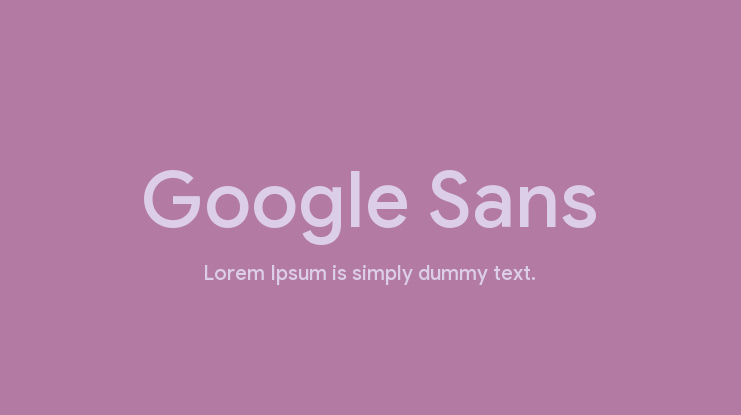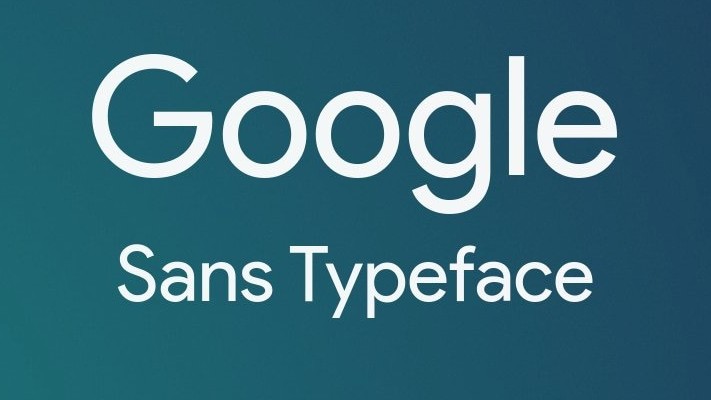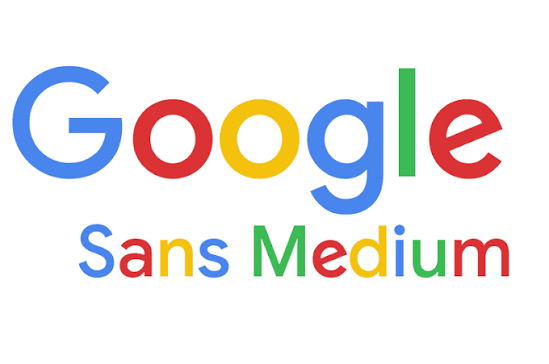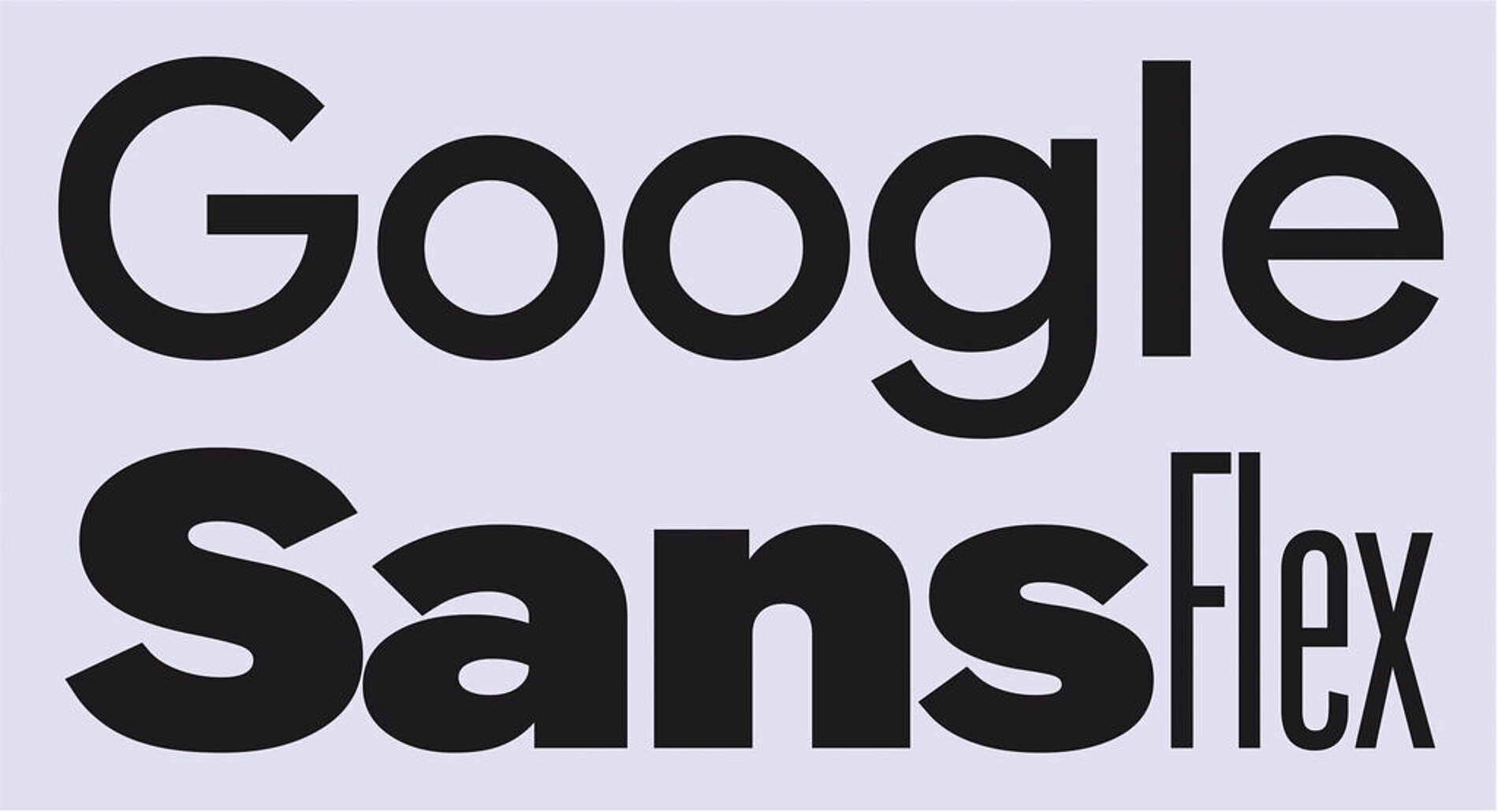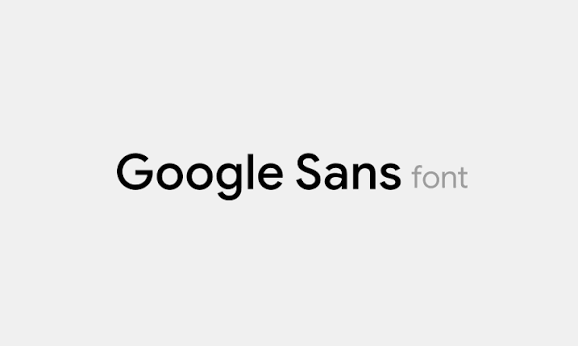
Google Sans là phiên bản tùy chỉnh của bộ phông Product Sans, được Google thiết kế tối ưu cho việc hiển thị trên đa dạng nền tảng từ thiết bị di động đến các ấn phẩm in ấn khổ lớn. Với cấu trúc hình học chuẩn xác và vẻ ngoài thân thiện, việc download font Google Sans giúp các nhà thiết kế, kiến trúc sư trình bày nội dung văn bản một cách chuyên nghiệp, hiện đại.
Google Sans
Sự tinh tế trong ngôn ngữ thiết kế của bộ font Google Sans
Điểm thu hút đặc trưng của Google Sans nằm ở sự cân bằng hoàn hảo giữa các đường nét hình học và tính nhân bản. Khác với những phông chữ không chân truyền thống thường có cảm giác hơi thô cứng, Google Sans sở hữu các góc bo nhẹ nhàng và khoảng hở giữa các chữ cái được tính toán khoa học. Phiên bản tải font Google Sans Việt hóa đã được xử lý kỹ lưỡng hệ thống dấu thanh tiếng Việt, giúp các ký tự đặc biệt phối hợp nhịp nhàng với thân chữ, duy trì vẻ đẹp tinh gọn và sang trọng của bộ gốc.
Sự ổn định về mặt thị giác còn giúp phông chữ này trở thành lựa chọn ưu tiên cho các nội dung cần độ minh bạch cao. Dù được sử dụng cho tiêu đề chính hay các đoạn thuyết minh kỹ thuật, bộ phông vẫn giữ được độ sắc nét và sự rõ ràng cần thiết. Đây là phương án hiệu quả để thể hiện tư duy sáng tạo hiện đại, phù hợp với xu hướng kiến trúc tối giản và các giải pháp xây dựng thông minh hiện nay.
| Phân loại phong cách | Geometric Sans-serif / Modern Style |
| Lĩnh vực phù hợp | Website, Portfolio dự án, Bảng hiệu công trình |
Tư vấn lựa chọn: Google Sans đạt hiệu quả thẩm mỹ cao khi bạn sử dụng các biến thể Bold cho tiêu đề chính và Regular cho nội dung chi tiết. Việc giữ khoảng trắng xung quanh văn bản rộng rãi sẽ giúp phông chữ này toát lên vẻ hiện đại và đẳng cấp cho bản thiết kế của bạn.
03 Ứng dụng đưa phông chữ Google vào thực tế xây dựng
Nhờ diện mạo khoa học và dễ tiếp nhận, việc sử dụng các kiểu chữ từ google download font mang lại giá trị thực tế cao trong quá trình triển khai dự án:
- Hệ thống nhận diện cho Homestay & Nhà lắp ghép: Những đường nét hiện đại của Google Sans rất ăn ý khi xuất hiện trên biển tên phòng hoặc biển chỉ dẫn nội khu. Phông chữ này giúp không gian toát lên vẻ chỉn chu, chuyên nghiệp và cực kỳ thân thiện với du khách.
- Hồ sơ năng lực doanh nghiệp: Sử dụng tải font Google Sans giúp trình bày thông tin dự án, báo giá và giải pháp kỹ thuật một cách mạch lạc, tạo ấn tượng tốt về một đơn vị thi công có phong cách làm việc ngăn nắp.
- Ghi chú thông số trên bản vẽ phối cảnh: Độ rõ nét của phông chữ hỗ trợ đắc lực cho kiến trúc sư khi trình bày các chú thích về vật liệu panel, kết cấu thép hay chi tiết nội thất, giúp khách hàng dễ dàng nắm bắt ý tưởng thiết kế.
03 Lưu ý trình bày bố cục đạt tính thẩm mỹ cao với Google Sans
Để khai thác hiệu quả vẻ đẹp của bộ phông này mà không làm giảm tính chuyên nghiệp của bản thiết kế, người dùng nên lưu tâm một số kinh nghiệm kỹ thuật sau:
- Phân cấp thông tin bằng độ đậm: Hãy tận dụng biến thể Bold của Google Sans download font cho các đề mục lớn để tạo độ nhấn thị giác, giúp người đọc dễ dàng theo dõi mạch logic của tài liệu.
- Kiểm soát kích thước hiển thị: Font chữ này hiển thị cực tốt trên môi trường kỹ thuật số. Tuy nhiên, khi in ấn hồ sơ trên giấy, bạn nên kiểm tra độ sắc nét của các dấu thanh để đảm bảo các ký tự nhỏ không bị nhòe nét.
- Tính đồng bộ thương hiệu: Hãy duy trì sử dụng Google Sans xuyên suốt từ trang web giới thiệu giải pháp nhà container đến slide trình chiếu và biển hiệu thực tế tại công trình để tạo nên sự thống nhất trong hình ảnh thương hiệu.